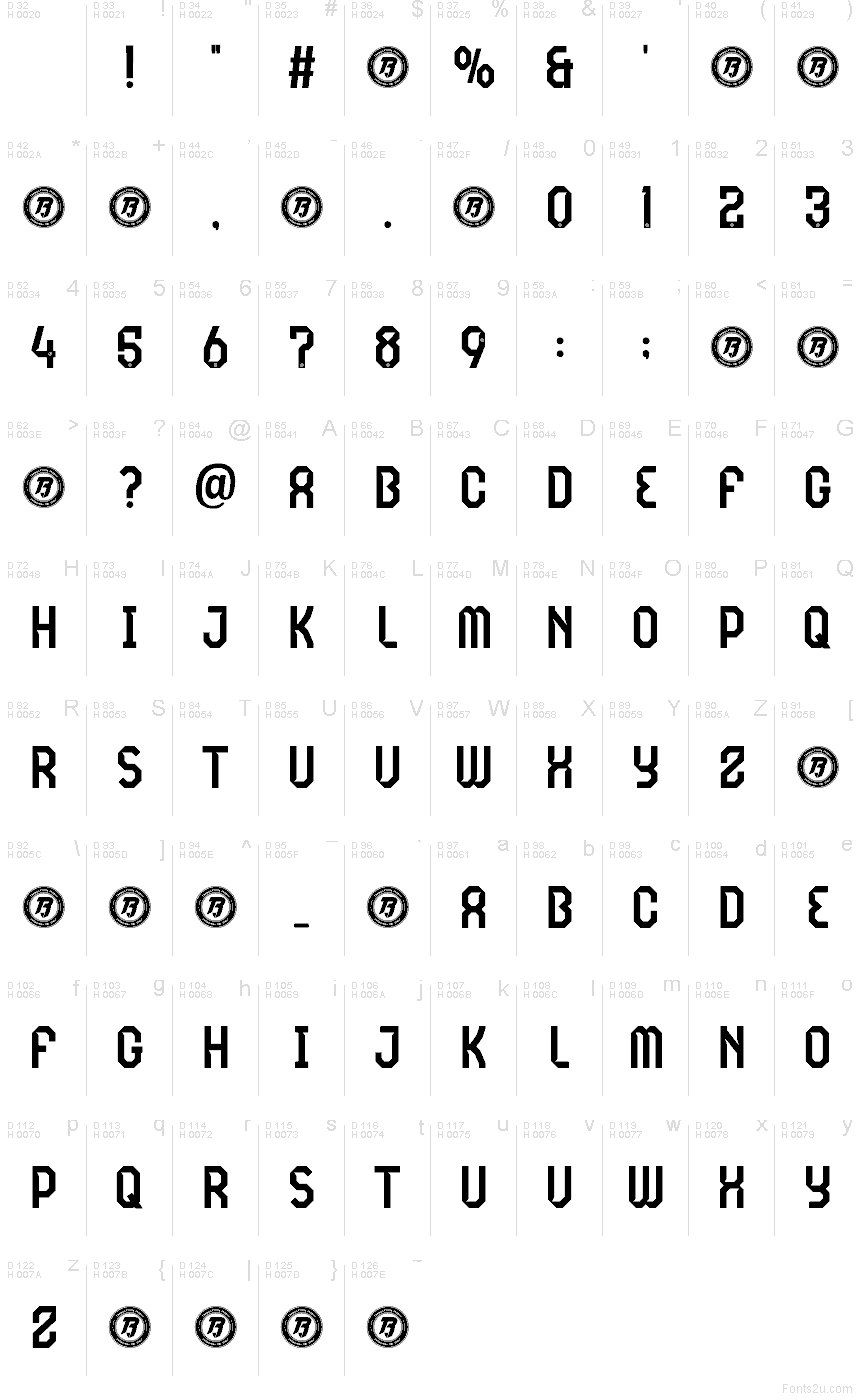
Feijenoord 2 de Trequartista Studio es una tipografía display gratuita de estilo techno-blackletter, con bordes marcados, muescas profundas y un ritmo contundente, casi como una bandera. Las mayúsculas parecen talladas bajo una misma geometría pesada, mezclando la esencia gótica con la actitud directa de un cartel de estadio.
Esta tipografía gratuita es ideal para branding deportivo, marcas de streetwear, pósteres musicales, títulos y portadas donde se requiere que las letras aporten carácter y solemnidad a partes iguales. Funciona de maravilla en monogramas y titulares cortos, ya que los cortes en zigzag y las formas macizas dan a cualquier palabra una presencia sólida y contundente.
Feijenoord Personal Use 2 — Presentación de la fuente